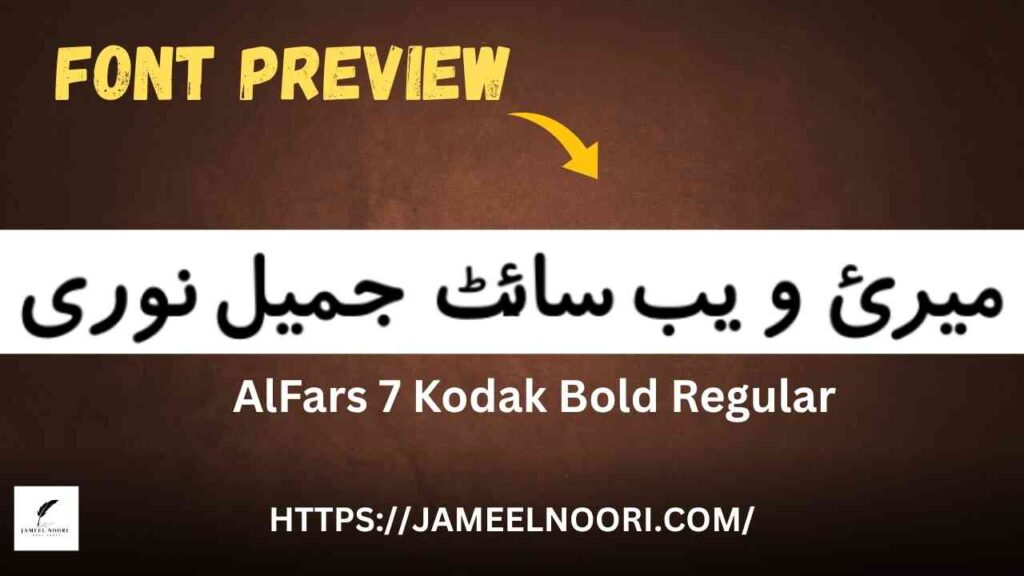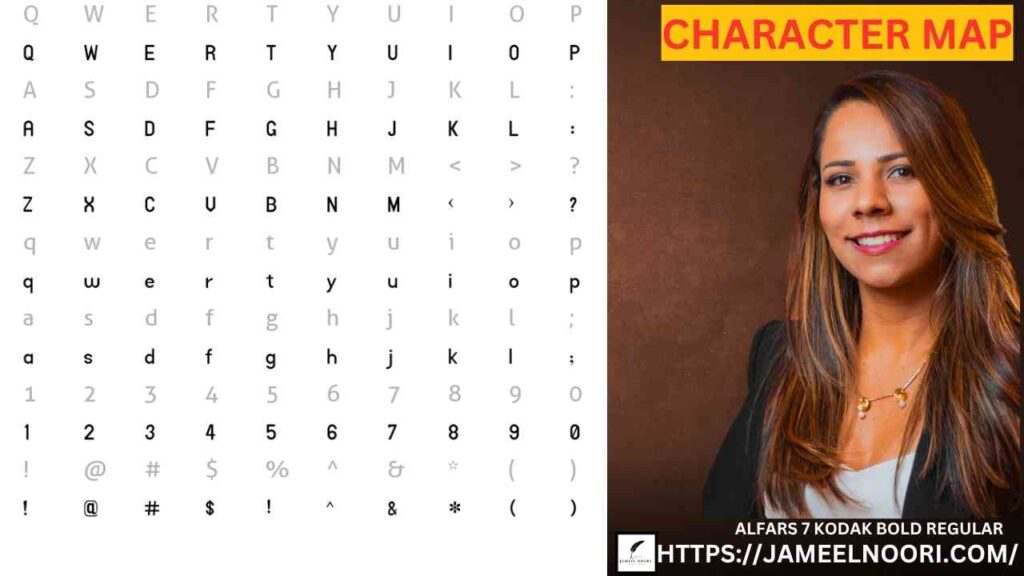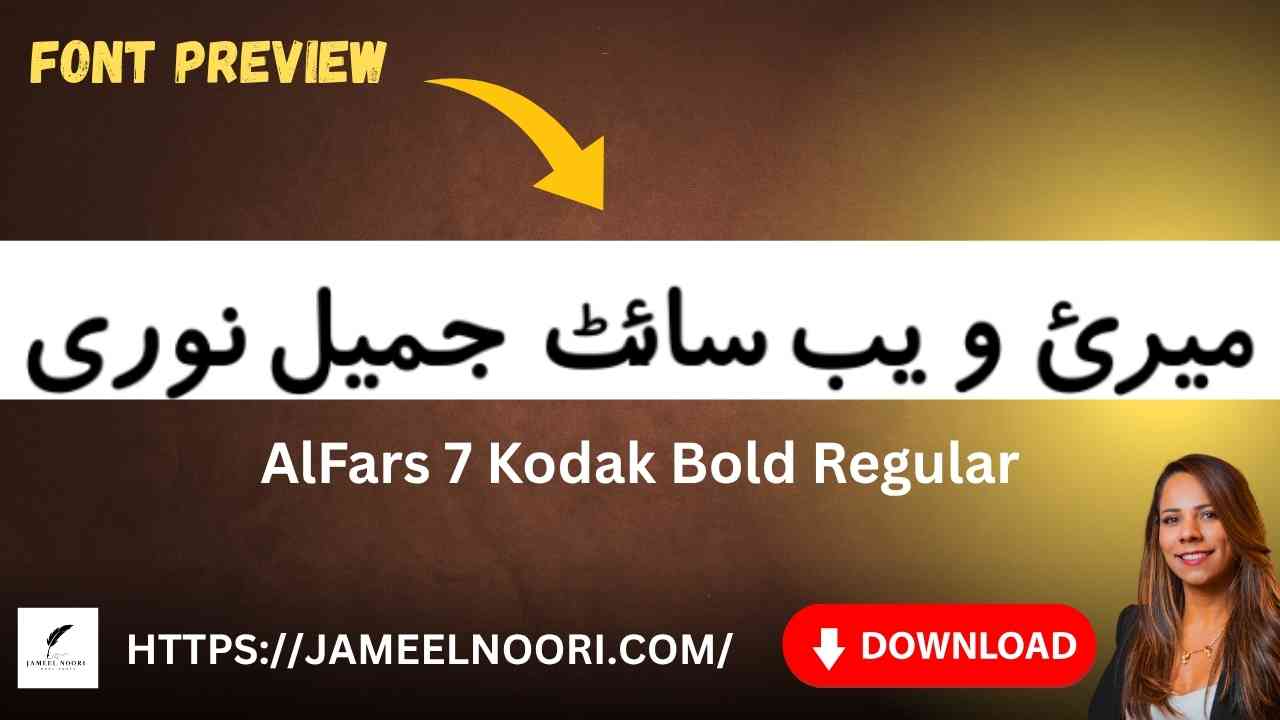
Introduction – Download Urdu Font AlFars Kodak Bold Regular-Urdu Font Kya Hai?
Agar aap ek bold aur impactful Urdu font ki talaash mein hain, to AlFars Kodak Bold Regular aapke design projects ke liye behtareen choice ho sakta hai.. Yeh font Urdu headings, posters, aur digital graphics ke liye specially design kiya gaya hai.. Ab tak isay 26,199 dafa download kiya gaya hai aur 34 users ne isay 4.16/5 star rating di hai..
AlFars 7 Kodak Urdu Font Ke Features
- ✅ Bold aur stylish Urdu typography
- ✅ Ideal for titles, banners, thumbnails, aur graphic design
AlFars 7 Kodak Bold Font Ka Istemaal Kahan Ho Sakta Hai?
Yeh font un designers ke liye best hai jo modern aur bold Urdu visuals banana chahte hain:
- 🎯 YouTube aur social media thumbnails
- 🎯 Urdu poetry aur quotes
- 🎯 Wedding cards aur event posters
- 🎯 School/college projects
- 🎯 Islamic calligraphy & brochures
❓ Kya is font mein Urdu glyphs hain?
✔️ Haan, yeh font Urdu characters ko modern aur bold design mein render karta hai..
Conclusion – Apne Design Ko Banayein Bold aur Stylish
AlFars Kodak Bold Regular Urdu Font un logon ke liye hai jo Urdu content ko strong visual appeal dena chahte hain.. Chahe aap ek YouTube creator hain, designer hain, ya blogger – yeh font har platform ke liye perfect hai.